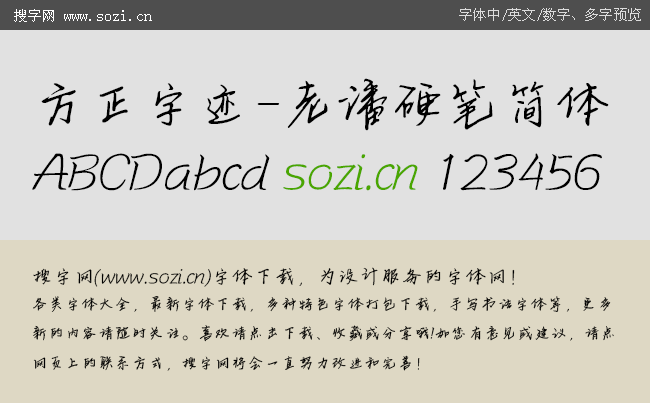
方正字跡-老潘硬筆簡(jiǎn)體手機(jī)字體包
搜字網(wǎng)給大家提供一款方正字跡-老潘硬筆簡(jiǎn)體手機(jī)字體包手機(jī)中文字體下載。這款手機(jī)字體是一款手寫(xiě)風(fēng)格的鋼筆字體,字體書(shū)寫(xiě)流暢,瀟灑大方。整體效果十分出色。喜歡的朋友趕快下載吧。